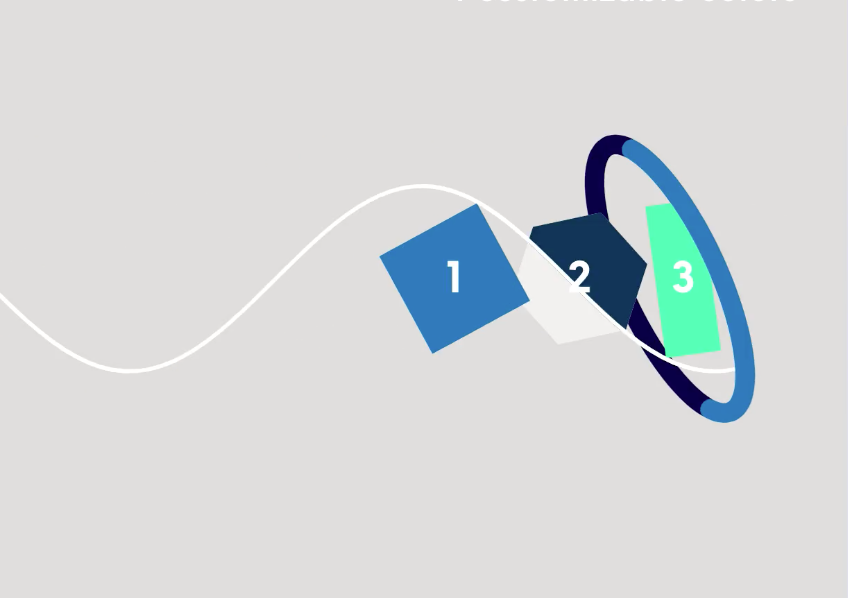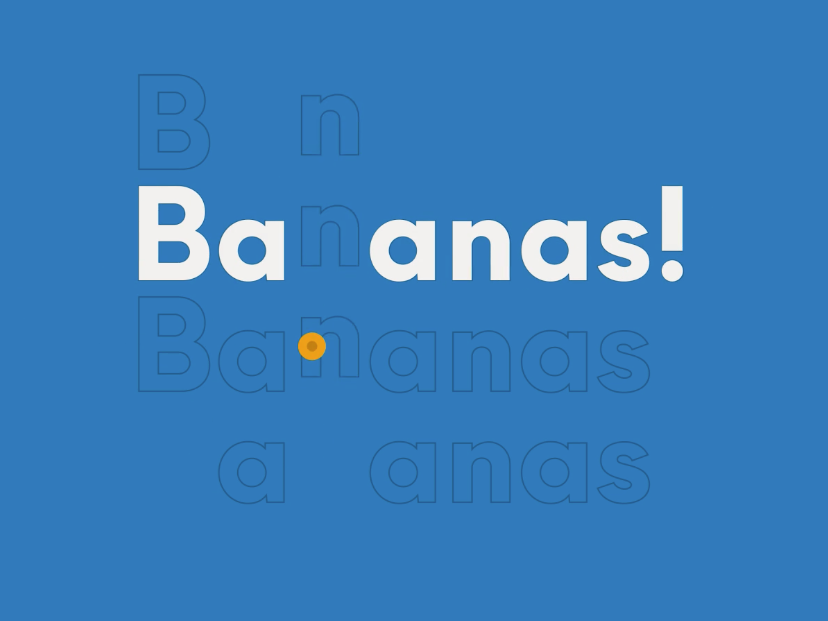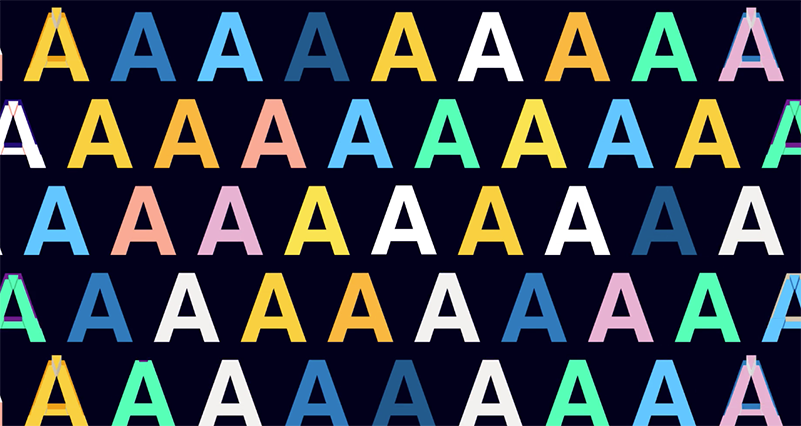
Mobilo Animated, la tipografía animada gratuita de Animography
Tipografía animada holandesa
Animography, la tienda online de tipografía animada, fundada y comisariada por el estudio de diseño y animación gráfica digital holandés, Calango, presenta Mobilo Animated. Se trata de una iniciativa que viene a sumarse a Franchise Animated (2013) y Animography Monthly (2014), dos proyectos que invitaban a diseñadores y artistas a trabajar e investigar sobre las infinitas posibilidades que ofrecen las tipografías animadas. Acompañado por Alfredo Marco Pradil de Hanken Co. —responsable del diseño de la tipografía— y Clark Rhee –autor de la música y el sonido–, Krielaars propone ahora explorar el equilibrio entre la aleatoriedad y el enfoque sistemático en el diseño de la tipografía animada.
Mobile Animated, la tipografía animada de Animography
236 animadores que dan vida a Mobilo Animated
La tipografía diseñada por Alfredo Marco Pradil es el punto de partida del trabajo de los 236 animadores que dan vida a Mobilo Animated. Responsable cada uno de un solo carácter y utilizando no más de cuatro colores y 25 marcos en una composición de 500 x 600 pixeles, los participantes han creado un alfabeto animado que, aunque reúne una gran variedad de técnicas y estilos, queda unificado por la paleta de colores y las formas utilizadas. Todas las letras y números tienen tres variantes únicas, lo que permite evitar la animación repetitiva en palabras con letras repetidas y proporciona la libertad de escoger y elegir «personajes que van bien juntos». El archivo After Effects, que contiene todos los fotogramas clave, expresiones y ilustraciones de los artistas, puede utilizarse en proyectos comerciales y no comerciales, y está disponible para su descarga desde la propia web por el precio de un Tweet o Facebook-post.
Mobile Animated, la tipografía animada de Animography
Visita indiscutible para cualquiera que esté buscando una tipografía animada para su proyecto, Animography ofrece letras ‘en movimiento’ muy fáciles de usar, que compatibles con After Effects CS5 y versiones posteriores, y preparadas para trabajar con characteristic (script de After Effects), pueden ser personalizadas y escaladas con total libertad, sin perder por ello su calidad original. Junto a las versiones ‘standard’ ofrece un servicio personalizado para clientes que no encuentran el tipo de letra que buscan o desean una licencia exclusiva. «Estudiando las distintas necesidades podemos crear una fuente estática y una de tipo animado desde cero que se ajuste a su marca, o utilizar sus tipos de letra estáticos actuales y animarlos» señalan los diseñadores. Además, todo aquel que esté trabajando en una fuente de animación y quiera venderla en Animography no tiene más que mandar un mail a hello@animography.net con la propuesta. Aunque lo ideal es enviar la tipografía después de haber hecho una prueba de animación de los primeros tres giflos, el equipo de Calango es consciente de que hay muchos diseñadores sin experiencia alguna en la animación. «Ofrecemos nuestra ayuda e invitamos a todos los interesados a que nos envíen sus archivos, que nosotros revisaremos para determinar si son adecuados para la animación» añaden desde la plataforma.
Mobile Animated, la tipografía animada de Animography